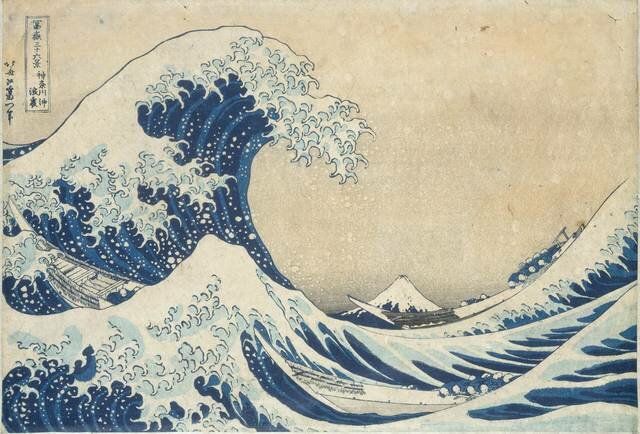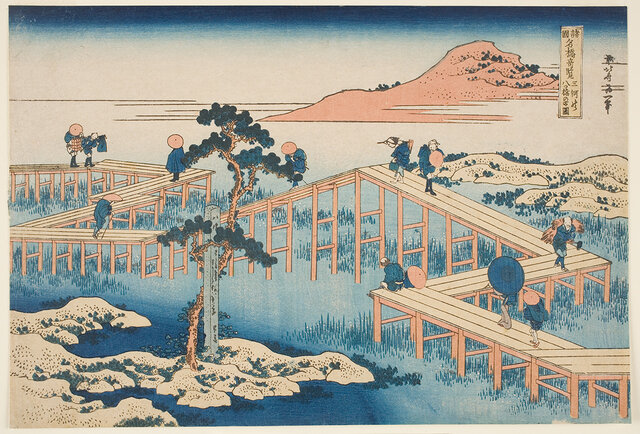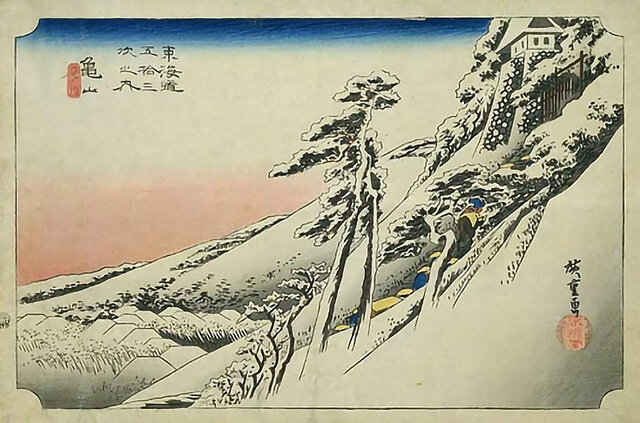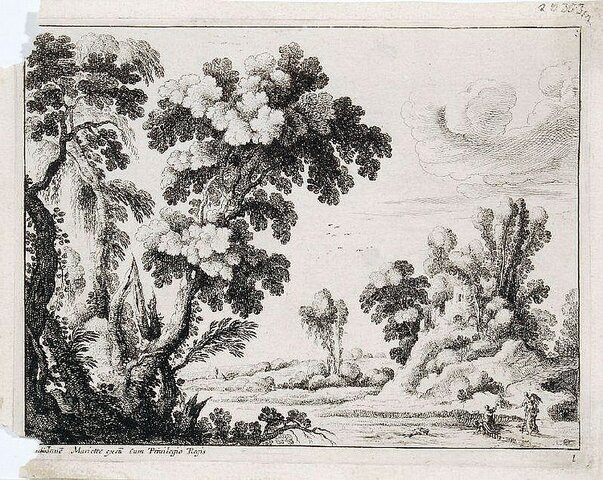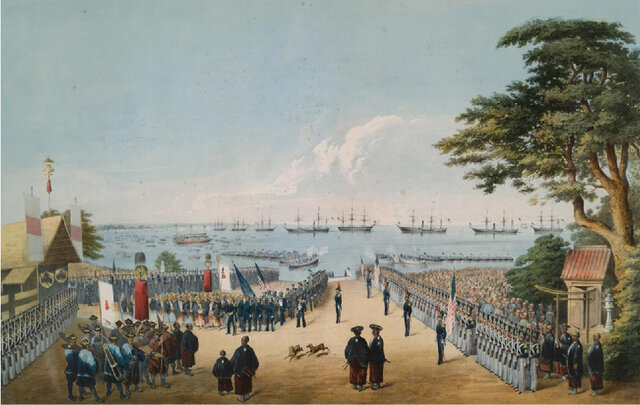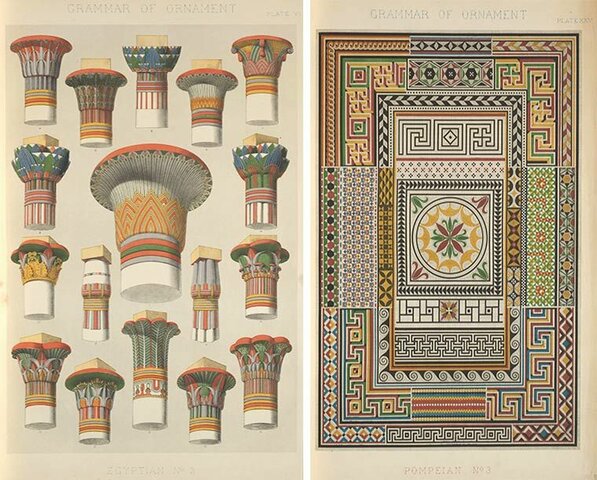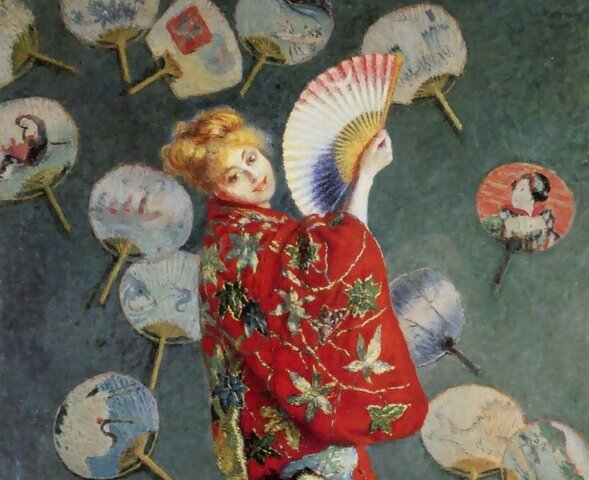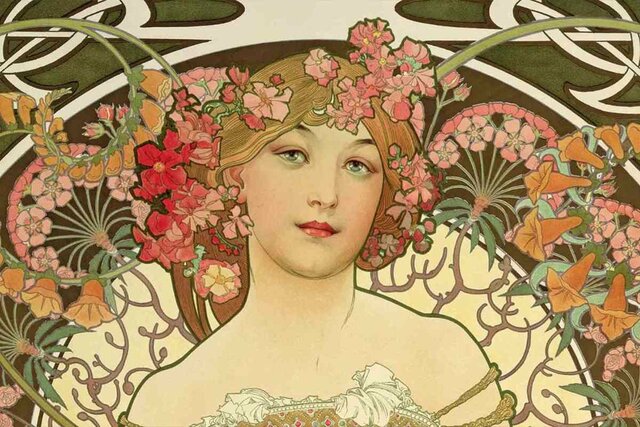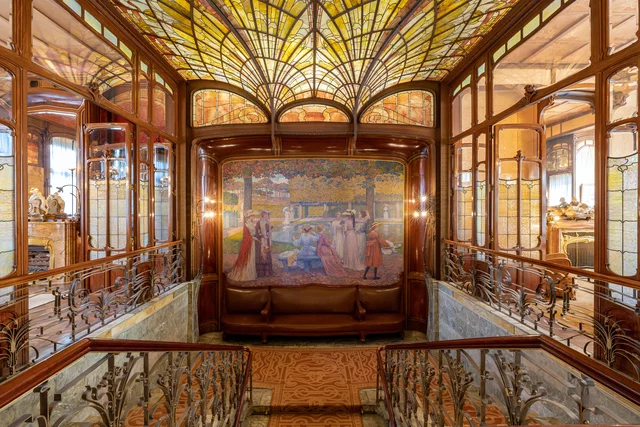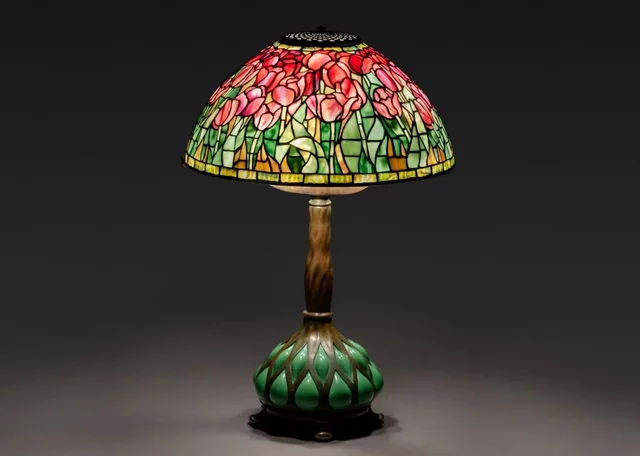
El Art Nouveau, la estampa y grabados japoneses, la Gramática de Ornamentos y la tipografía Troya.
Durante el siglo VII, la técnica de impresión de bloques de madera se introduce en Japón desde China, y años más tarde el emperador Shōmu ordena la creación de la colección de imágenes budistas conocida como "Man'yōshū" utilizando la técnica de impresión en bloques de madera. Esta técnica luego se convirtió en unas principales en Japón para la producción de textos religiosos y literatura popular. -
Comienza el período Edo y se establece el gobierno Tokugawa. Se desarrolla el ukiyo-e, un género de estampas populares que retratan escenas de la vida cotidiana, paisajes, actores de teatro kabuki y hermosas mujeres.
Más tarde, Hishikawa Moronobu, a menudo considerado el primer artista profesional de ukiyo-e, comienza a producir estampas en bloques de madera. Este arte se popularizó en Japón durante en este tiempo, siendo adaptado y adoptado como un medio para producir impresiones en masa. -
El comerciante alemán Engelbert Kaempfer publica un libro en Europa que contiene descripciones y grabados de estampas japonesas, lo que marca uno de los primeros intentos de introducir el arte japonés en el continente. Unos años más tarde, se publica en Francia el libro "Le Japon à la Mode" de Pierre-Jean Mariette, que incluye una serie de estampas japonesas. Esta publicación despierta el interés y la curiosidad por el arte japonés. -
Tsutaya Jūzaburō, un editor de libros, inicia la producción de libros ilustrados, lo que lleva al desarrollo de series de estampas que representan paisajes, lugares famosos y las estaciones del año. A finales del siglo XVIII, artistas como Suzuki Harunobu, Kitagawa Utamaro y Katsushika Hokusai se destacan en el ukiyo-e, creando obras conocidas por su belleza, expresión y experimentación técnica. -
Durante el siglo XIX, Hiroshige Utagawa produce su serie "Las cincuenta y tres estaciones del Tokaido", estableciéndose como uno de los principales artistas del ukiyo-e y destacando su enfoque innovador en la composición y los efectos atmosféricos. Además, Hokusai publica su obra maestra "Treinta y seis vistas del monte Fuji", que incluye la icónica estampa "La gran ola de Kanagawa". -
Las estampas y grabados japoneses comienzan a importarse a Europa, donde ejercen una profunda influencia en artistas y diseñadores. Estos grabados se caracterizaban por el uso de colores vivos, formas simplificadas y composiciones dinámicas. Influyeron profundamente en el desarrollo del Art Nouveau, que tomó prestados muchos de sus elementos estilísticos del arte japonés. -
El comodoro Matthew Perry lidera una expedición estadounidense a Japón con el objetivo de establecer relaciones comerciales. Esta apertura de Japón al mundo occidental desencadena una mayor llegada de estampas japonesas a Europa, lo que tiene un impacto en el Ukiyo-e al introducir nuevos temas y estilos influenciados por el arte europeo. -
Se publica The Grammar of Ornament, un libro de Owen Jones. El libro es un estudio exhaustivo de la ornamentación de todo el mundo, y se convierte en un recurso esencial para los diseñadores del Art Nouveau. El libro de Jones fue el primero en clasificar y analizar sistemáticamente el ornamento, y proporcionó a los diseñadores del Art Nouveau una gran fuente de inspiración. -
Las estampas japonesas comienzan a influir en artistas europeos, particularmente en Francia, donde el movimiento artístico conocido como Japonismo se desarrolla en respuesta a la fascinación por el arte japonés. En 1862, se realiza una exposición de arte japonés en Londres, que incluye estampas y otros objetos japoneses. Esto aumenta el conocimiento y la apreciación del arte japonés en Europa. -
En París, se lleva a cabo la Exposición Universal, donde se exhiben estampas japonesas, lo que genera un gran impacto en los artistas y diseñadores europeos. Para finales de siglo, artistas como Vincent van Gogh, Édouard Manet, Edgar Degas, Henri de Toulouse-Lautrec y James Abbott McNeill Whistler, entre otros, se ven influenciados por las estampas japonesas en su estilo y enfoque artístico. -
Comienza en Europa el movimiento Art Nouveau, caracterizado por el uso de formas curvilíneas, motivos orgánicos y ornamentación estilizada. El movimiento se inspiró en diversas fuentes, como el arte japonés, el arte celta y el movimiento Arts and Crafts. El término "Art Nouveau" se utiliza por primera vez en Bélgica, en la revista "L'Art Moderne". Artistas y diseñadores buscaban romper con las convenciones tradicionales y explorar nuevas formas de expresión. -
El movimiento Art Nouveau comienza a ganar popularidad en Europa. Caracterizado por sus formas orgánicas y curvas, se convierte en un estilo dominante en la arquitectura, el diseño de interiores, las artes gráficas y la joyería. Además, comienza a extenderse a otras partes del mundo, como Estados Unidos, Canadá y Australia. -
La tipografía Troya fue diseñada por William Morris. Fue inspirada en la caligrafía medieval y se convirtió en una de las tipografía Art Nouveau más populares. Se caracteriza por sus formas altas y estrechas, con detalles intrincados y un generoso espaciado entre caracteres. Su objetivo era capturar la elegancia y legibilidad de los primeros libros impresos. Se utilizó mucho en el diseño de libros, la publicidad y otras aplicaciones de las artes gráficas. -
Aunque la era del Art Nouveau fue relativamente breve, su legado perdura en la historia del arte y el diseño. Su enfoque innovador, su énfasis en la naturaleza y su estilo ornamental han dejado una marca duradera en la estética y la apreciación del arte y el diseño hasta el día de hoy.